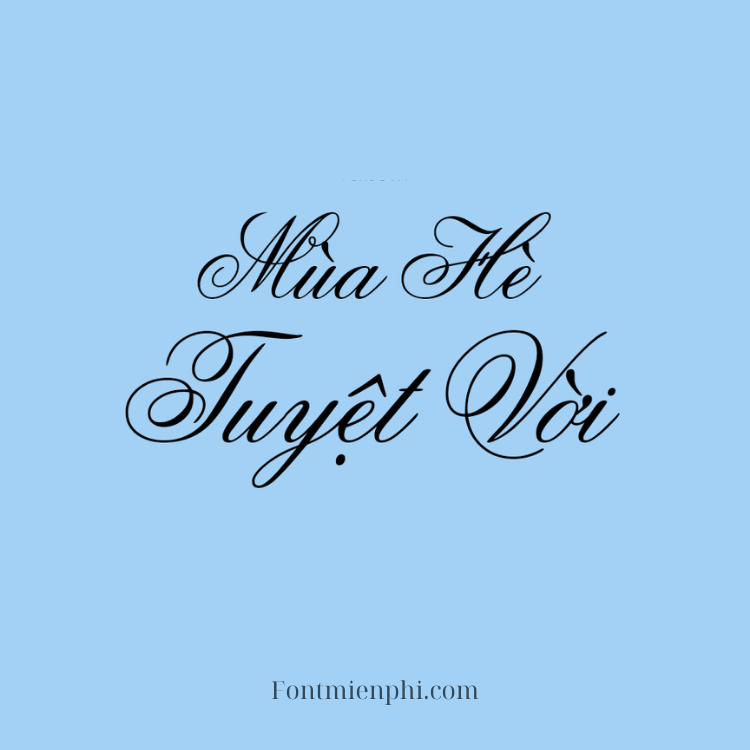
Font Việt hóa VIP Nura Asyifa
Font Việt hóa VIP Nura Asyifa – Nét chữ nghệ thuật tinh tế dành cho thiết kế chuyên nghiệp
Giới thiệu về Font Việt hóa VIP Nura Asyifa
Trong thế giới thiết kế đồ họa, việc lựa chọn một bộ Font Miễn Phí chất lượng luôn là ưu tiên hàng đầu của các nhà sáng tạo. Font Việt hóa VIP Nura Asyifa nổi lên như một sự lựa chọn hoàn hảo nhờ phong cách Script hiện đại xen lẫn nét cổ điển quý phái. Bộ phông chữ này không chỉ mang lại vẻ đẹp thanh lịch mà còn được tối ưu hóa hoàn toàn cho tiếng Việt, giúp người dùng không còn lo lắng về lỗi hiển thị dấu câu hay các ký tự đặc biệt trong quá trình làm việc.
Đặc điểm nổi bật của Font Việt hóa VIP Nura Asyifa
Thiết kế mềm mại và linh hoạt
Font Việt hóa VIP Nura Asyifa sở hữu những đường nét uốn lượn uyển chuyển, tạo cảm giác như được viết bằng tay một cách tỉ mỉ. Các nét thanh và nét đậm được kết hợp hài hòa, giúp văn bản trở nên sống động và có chiều sâu hơn. Đây là công cụ đắc lực để tạo nên những sản phẩm mang đậm dấu ấn cá nhân và sự tinh tế nghệ thuật.
Ứng dụng đa dạng trong thực tế
Nhờ vẻ ngoài sang trọng, bộ font này cực kỳ phù hợp cho các dự án thiết kế thiệp cưới, bìa sách, logo thương hiệu cao cấp hoặc các ấn phẩm truyền thông trên mạng xã hội. Sự linh hoạt của nó cho phép người dùng biến hóa phong cách từ hiện đại trẻ trung đến cổ điển trang trọng một cách dễ dàng nhất.
Kết luận và trải nghiệm người dùng